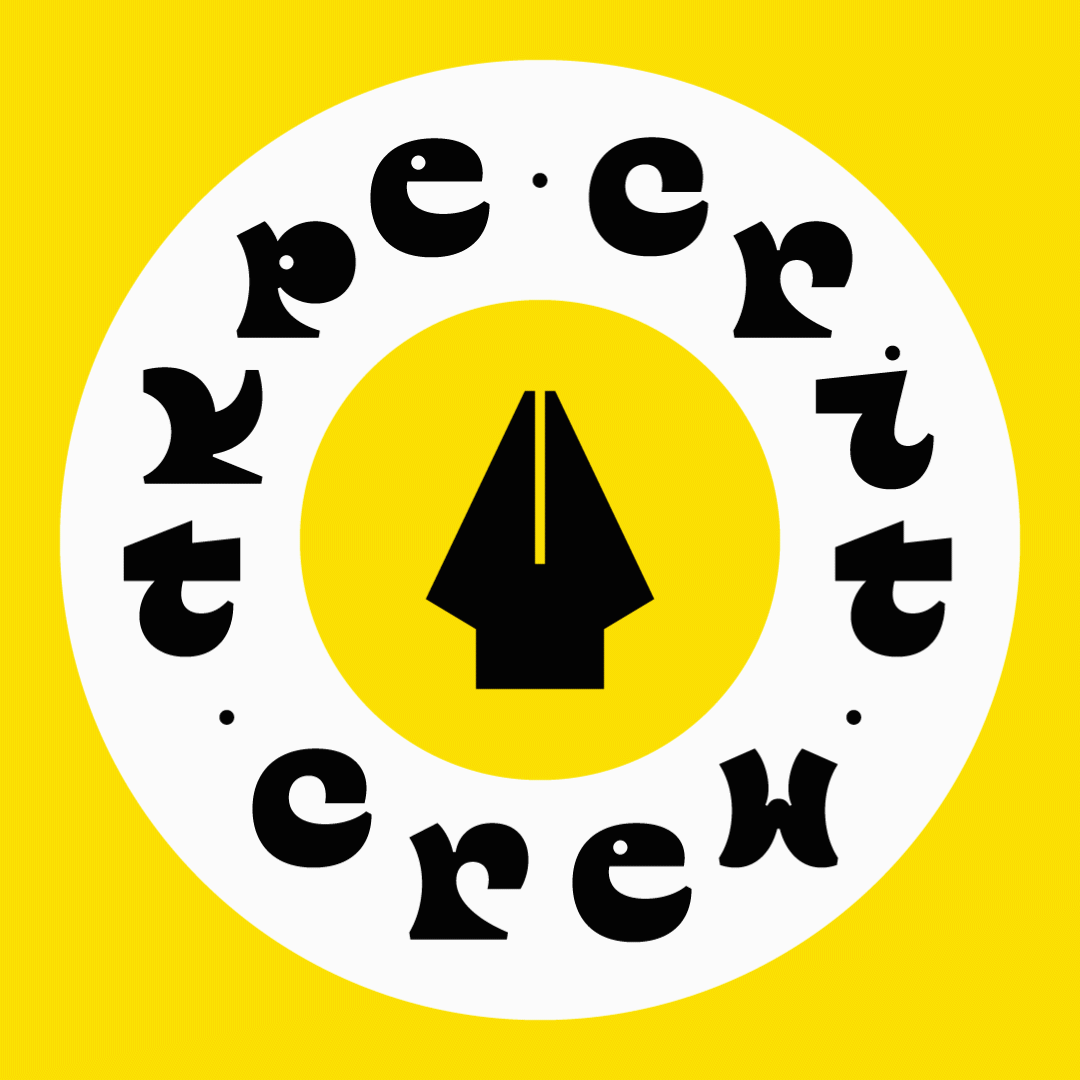
Nie zuvor wurde Typografie so stark als „Markenerlebnis“ genutzt wie heute.
Eine Reise zwischen Typografie, Kultur und Identität.
Juan Villanueva beschäftigt sich in seiner Arbeit in einzigartiger Weise mit den Schnittstellen zwischen Technologie, Kunst, Kultur und Identität. Juan lebt in New York City und ist Senior Type Designer bei Monotype. Als Letterer und Dozent setzt er sich mit Leidenschaft für die Förderung von Gemeinschaft und Barrierefreiheit ein, insbesondere mit Blick auf marginalisierte Gruppen.
Erste kreative Erfahrungen sammelte Juan beim Zeichnen von Animes und Nachzeichnen von Karikaturen aus Zeitschriften. Seine Eltern förderten seine kreative Ader, indem sie ihm die nötigen Materialien zur Verfügung stellten, und legten so den Grundstein für Juans Zukunft im Bereich Design. Sein Interesse an Technologie und Wissenschaft führte ihn in Kombination mit diesen frühen Erfahrungen zur Typografie: eine Disziplin, die Kunst, Kreativität und die Fähigkeit zur Lösung technischer Probleme im Gestalten von Buchstabenformen und Schriften vereint. Es ist diese einzigartige Verbindung aus künstlerischem Ausdruck sowie technischer Präzision und technischem Potenzial, für die Juan brennt.
Ich bin immer auf der Suche nach neuen kreativen Herausforderungen, besonders dort, wo Kunst, Technologie und Handwerk aufeinandertreffen.
Juans Herangehensweise ist geprägt von seiner Identität, seinem kulturellen Erbe und seiner Leidenschaft für Politik, Kunst und Design, entwickelt sich dabei jedoch stets weiter. Juan begnügt sich nicht mit einem einzigen Stil, sondern betrachtet seine Designreise als kontinuierliches Experimentieren mit und Entdecken von neuen Themen. Inspiration findet er hierbei in unterschiedlichsten Einflüssen: von der rohen, unvollendeten Ästhetik des Death-Metal-Letterings bis hin zu den Schnitztechniken und den filigranen Texturen des Linolschnitts. Besonders beeindruckt haben ihn die Schnitte, die er jüngst in einer Ausstellung der Arbeiten von Elizabeth Catlett im Brooklyn Art Museum gesehen hat.
Als peruanischer Einwanderer aus Lima, der nun in New York City lebt, erlebt Juan die komplexen Wechselwirkungen zwischen Identität und Einwanderung täglich. Wie Juan berichtet, ist es nicht immer leicht, inmitten eines so vielfältigen Umfelds die eigene Identität zu finden: „In dieser riesigen Masse aus den unterschiedlichsten Menschen, die dich manchmal sehen und manchmal nicht, du selbst zu sein, ist herausfordernd.“ Zugleich sieht Juan darin aber auch etwas Schönes. Schriftgestaltung ist für ihn ein wirkungsvolles Instrument, um diversen Geschichten und Stimmen eine Bühne zu bieten. In seiner Tätigkeit als Dozent legt er besonderen Wert darauf, Räume zu schaffen, in denen marginalisierte Stimmen ihre Geschichte teilen und sich somit auch in der größeren Welt der Schriftgestaltung bemerkbar machen können.
Dieses Verständnis von Schrift als kreatives Ventil für Identität und Ausdruck prägt seine professionelle Arbeit. Als Schriftgestalter, der täglich mit großen Marken zusammenarbeitet, betrachtet er Schrift als entscheidenden Faktor, der bei der Vermittlung der Markenwerte genauso wichtig ist wie Farbe, Fotografie und Ton.
Gute Typografie wird von ihrem Kontext bestimmt. Jeder Kunde ist einzigartig, und gute Typografie zielt vor allem darauf ab, die perfekte Kombination aus typografischen Stilen zu finden, durch die unsere Kunden eine Bindung zu ihrer Zielgruppe aufbauen können.
Diese subtilen, emotionalen Aspekte von Schrift haben schon immer entscheidend zu ihrer Wirkung beigetragen, und daran wird sich nach Juans Meinung auch nichts ändern. In Bezug auf Trends beobachtet er eine wachsende Vorliebe für Designs, die wie handgefertigt aussehen und dadurch eine menschliche Note haben. Er führt diese Entwicklung auf eine Gegenbewegung zu KI zurück. „Ich glaube, dass dieser Trend besonders auf der Idee basiert, dass ‚KI das noch nicht kann, also übernehmen wir es‘. Das Schlüsselwort lautet hierbei noch. Denn auch wenn KI vermutlich irgendwann lernen wird, diese Eigenschaften nachzuahmen, werden die Grenzen des Möglichen weiterhin von kreativen Menschen ausgelotet. Es wird also immer ein noch geben, das die KI erst einholen muss.“
Juans persönliche Philosophie diesbezüglich bildet auch die Grundlage für seinen Tipp mit Blick auf die Zukunft: „Warte nicht, bis es zu spät ist.“ „Wenn du eine Idee hast und ihr ohne weitere Probleme nachgehen kannst, dann tue es gleich.“ „Es passiert so viel in der Welt. Aber wenn du ein Projekt hast, das deiner mentalen Gesundheit zuträglich ist, von dem andere profitieren können oder das dir einfach nur Freude bereitet, dann warte nicht auf den ‚perfekten‘ Augenblick. Die Freude und der Mehrwert deines Projekts für dich, deine Liebsten oder deine Community sind unbezahlbar.“
Die Freude und Wirkung, die es Ihnen und allen, die Ihnen wichtig sind, sowie der Gemeinschaft bringen kann, ist unbezahlbar.
Juan ist Mitgründer von Sonotype, einem Tool, das im Rahmen des Projekts ‚Sound & Vision‘ entwickelt wurde und Designschaffenden und Marken dabei hilft, die richtige Musik und die passenden Fonts zu finden.